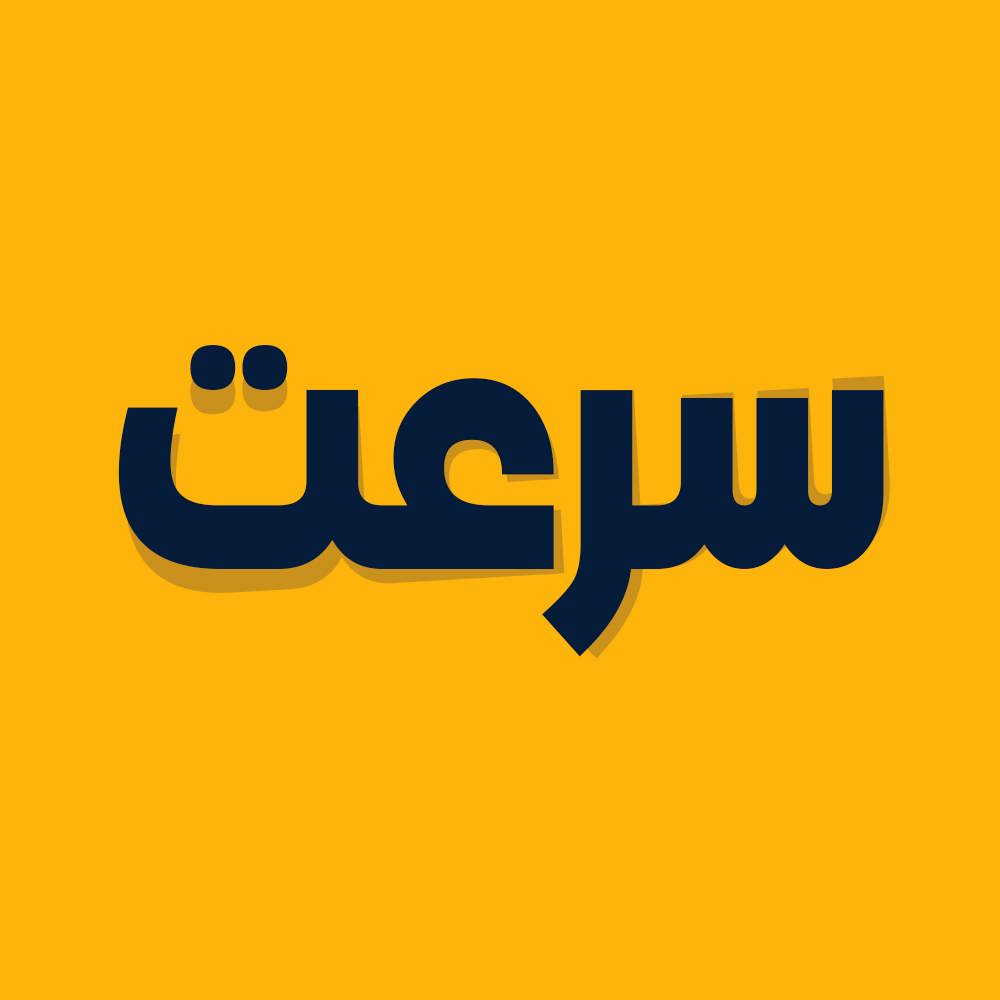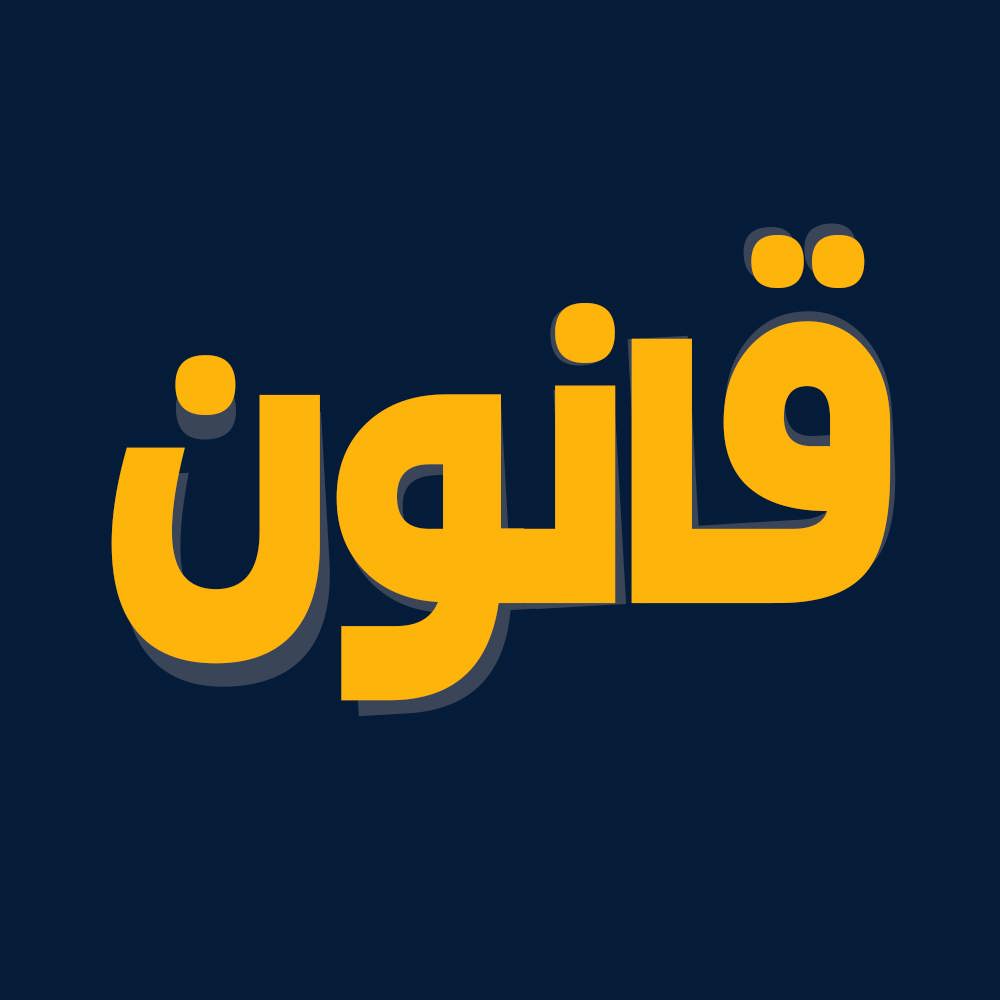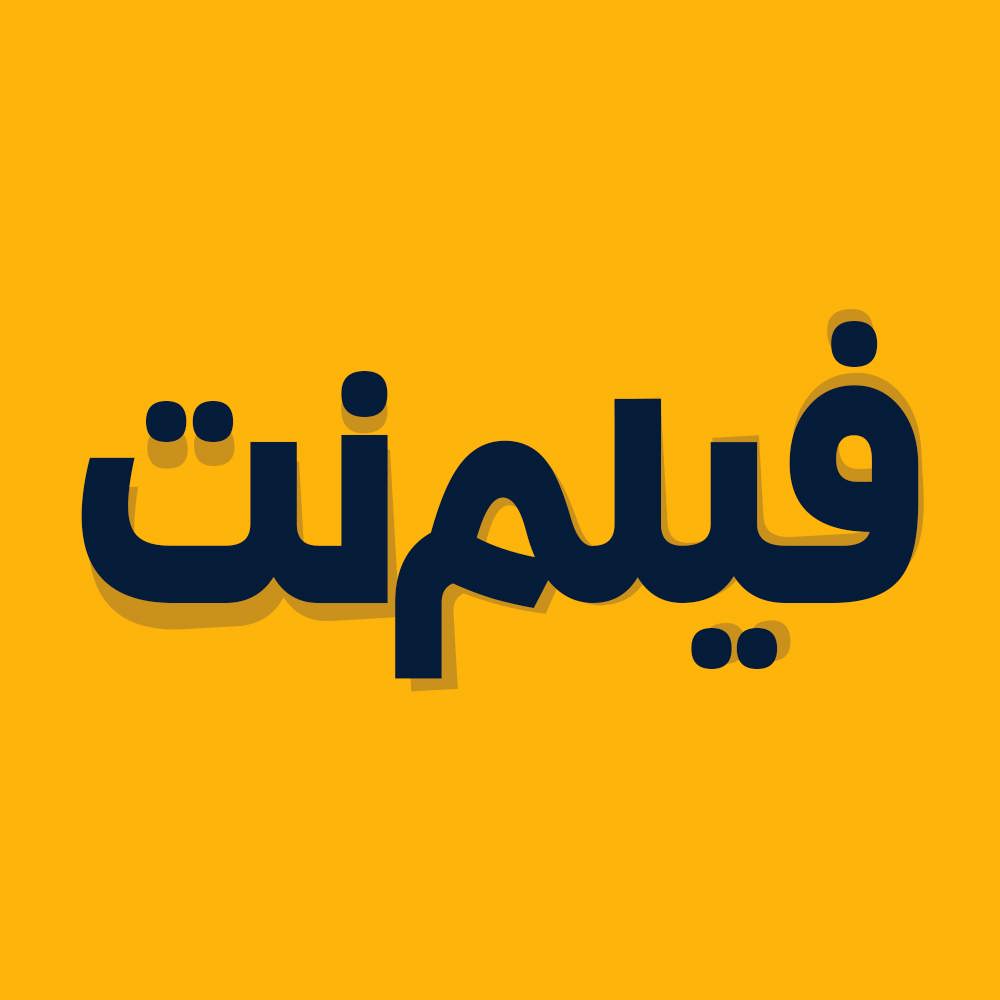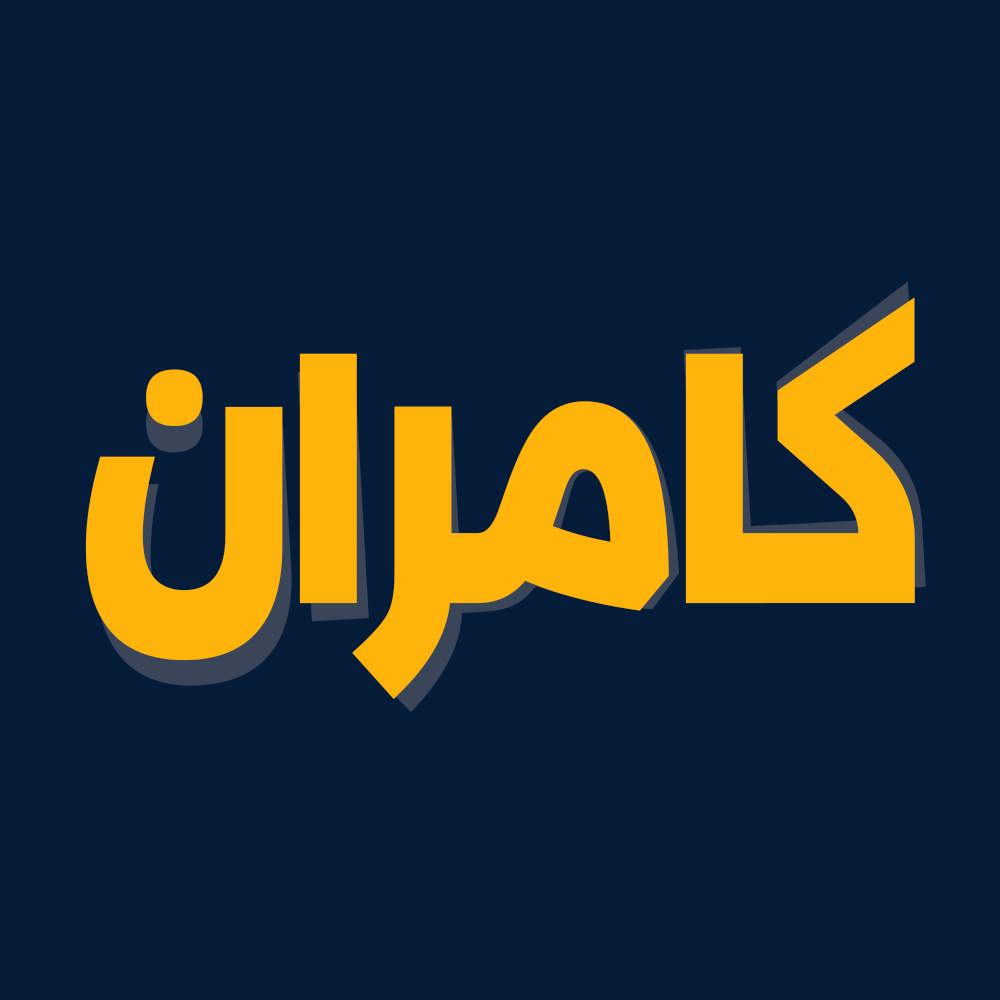
فونت فارسی آزمایش Azmayesh Font
فونت فارسی آزمایش یک فونت تک وزن با کاربرد طراحی لوگوتایپ و طراحی های مختلف همچون کتاب و تولید محتوای متن های کوتاه و عناوین می باشد. این فونت با ظاهر ساده و حرفهای خودش یه انتخاب عالیه برای طراحهایی که به وضوح و زیبایی اهمیت می دهند از طراحی رابط کاربری گرفته تا پروژههای چاپی. همچنین از این فونت در طراحی تابلوهای چلنیوم هم به دلیل ساختار منحصر به فردش می توانید استفاده کنید. در ادامه برای شما نمونه تایپ های این محصول حرفه ای رو آماده کردیم که میتونید مشاهده کنید.
پیشنمایش و نمونه تایپ های فونت آزمایش